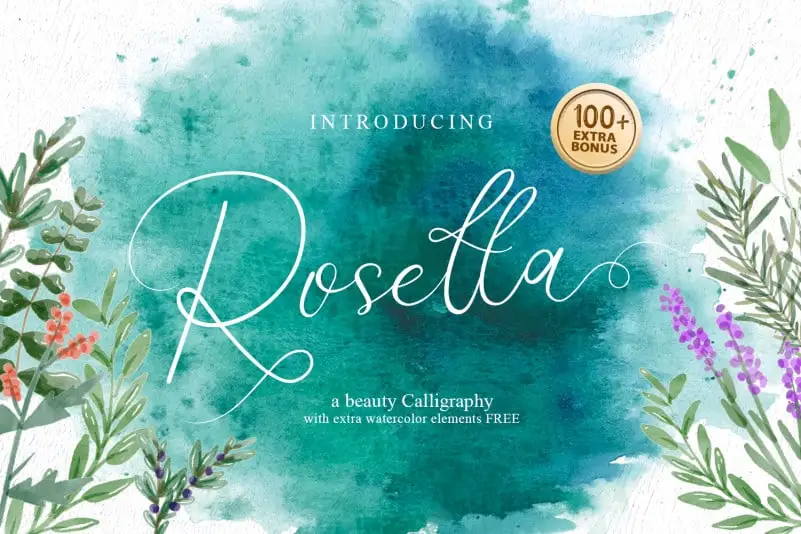
Rosetta Calligraphy Font – Download Grátis
Rosetta Calligraphy Font é uma elegante escolha para qualquer projeto que busque a perfeição do design manual. Sua origem italiana e persa lhe confere um toque refinado, enquanto suas múltiplas alternativas de estilo garantem uma variedade incrível. Associada ao antigo Roseta Stone, essa fonte é como um formiguinha elegante no cabelo de Rosa, sempre alegre e bonito. Rosetta é perfeita para cartões personalizados ou letras decoradas em livros, oferecendo uma graça natural que combina harmoniosamente com qualquer projeto. Com sua elegância perfeita, ela se destaca como o escolhido para quem busca um toque sofisticado e pessoal nas suas criações.
Designer: HydricDesign